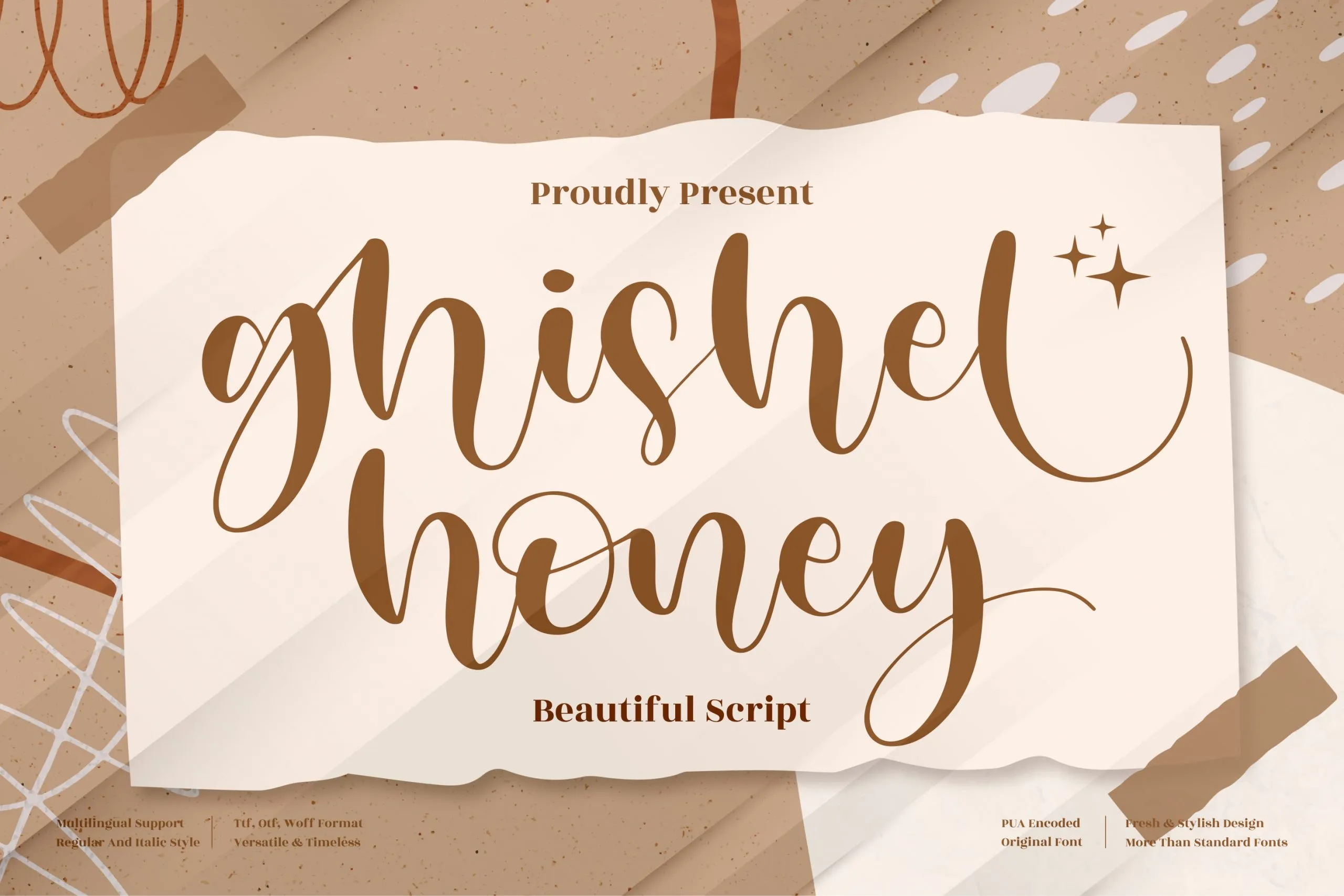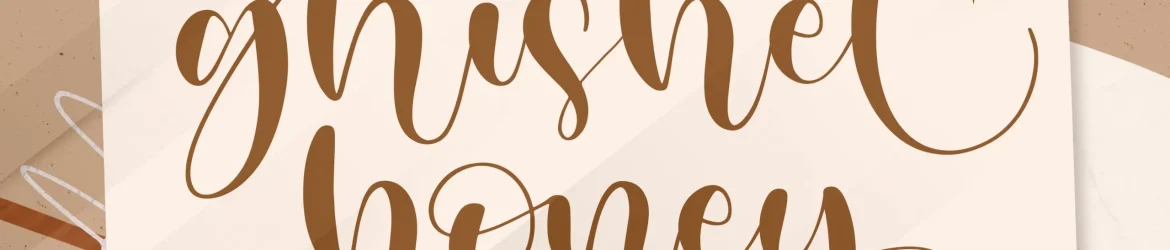
Ghisel Honey Font – Download Grátis
Esta é uma fonte de calligrafia romântica perfeita para projetos diversos que buscam uma escrita delicada e atraente. Perfeitamente adaptável a um vasto leque de criações, incluindo logotipos, identidade corporativa, designs de mobiliário, embalagens de produtos, taças personalizadas, mensagens e posters, sacolas de shopping, camisetas estampadas, capas de livros, cartões de nome, cartões de convite, cartelas para presentes, etiquetas, fotografias, marcos no papel e eventos especiais. Seja qual for seu projeto requintado que necessita de uma pitada de elegância script, esta fonte é perfeita para você. Desenvolvida pelo designer perspectype, a Ghisel Honey Font se destaca por sua graça e harmonia, oferecendo um toque sofisticado às suas criações. Ideal tanto para o design gráfico quanto na personalização de objetos cotidianos, essa fonte atende aos mais variados gostos e necessidades do mercado moderno, transformando suas ideias em obras que encantam e impressionam.